Canvaでかわいい日本語の手書きフォントってあるの?
おしゃれなデザインを作りたいけど、フォントが多すぎて迷いますよね。
実は、無料で使える手書きフォントを知っておけば、もっと簡単に理想のデザインが作れるんです!
看護師として働きながら、副業でブログやSNS運用をしている方も増えていますよね。
おしゃれなアイキャッチやバナーが作れれば、ブログのアクセスアップやSNSでの発信力も強化できます。
でも、なんとなくフォントを選んでしまうと、「イメージと違った…」と後悔することも。
フォント選びはデザインの印象を左右する大事なポイントなんです。
そこで今回は、Canvaで無料で使えるおしゃれでかわいい日本語手書きフォント7選を紹介します!
- Canvaで無料で使えるおすすめの手書きフォント
- ブログやSNSで使えるおしゃれなデザインのコツ
- フォント選びで失敗しないためのポイント
Canvaで無料で使えるおしゃれな日本語手書きフォントとその魅力
Canvaでデザインを作るとき、フォント選びは重要なポイントですよね。
特に手書き風フォントは、温かみや個性を演出するのにぴったりです。
無料で使えて、おしゃれでかわいい日本語の手書きフォントがあると、デザインの幅がぐっと広がります。
どんなフォントがあるのか、詳しく見ていきましょう。
手書きフォントの魅力や、Canvaで使うメリットを詳しく解説していきます。
初心者でも簡単におしゃれなデザインが作れるコツもご紹介しますね。
手書きフォントとは?特徴と魅力
手書きフォントは、その名の通り手書き風の文字を再現したフォントのこと。
活字フォントに比べて、温かみや親しみやすさがあり、デザインに柔らかい印象を与えます。
特に女性向けのデザインや、ナチュラルな雰囲気を出したいときにぴったりです。
例えば、ハンドメイドのロゴや、カフェのメニュー表などに使うと、おしゃれでかわいい雰囲気を演出できますよ。
Canvaで手書きフォントを使うメリット
Canvaはフォント選びが簡単で、デザインにすぐ反映できるのが魅力。
無料で使える手書きフォントも多く、商用利用可能なものもあるため、ブログのバナーやSNSの投稿など幅広い用途で活用できます。
特に、ドラッグ&ドロップで直感的に操作できるので、初心者でも使いやすいですね。
また、手書きフォントを使うことで、オリジナリティのあるデザインが簡単に作れますよ。
デザイン初心者でも使いやすい理由
「おしゃれなデザインを作りたいけど、センスに自信がない…」そんな方でも安心!
Canvaには、手書きフォントに合うテンプレートが豊富に用意されています。
そのままフォントを差し替えるだけで、洗練されたデザインに仕上げられるのが魅力ですね。
さらに、手書きフォントは「ラフな雰囲気」を演出しやすく、少しくらい配置がずれてもおしゃれに見えるのもポイントです。
手書きフォントなら、初心者でも簡単におしゃれなデザインが作れますね!
おしゃれでかわいい日本語手書きフォントおすすめ7選
Canvaには、おしゃれでかわいい日本語の手書きフォントがたくさんあります。
その中でも、無料で使えてデザインに取り入れやすいフォントを厳選しました。
手書きフォントの種類によって、ナチュラルな雰囲気からポップで元気な印象まで表現できます。
あなたのデザインにぴったりのフォントを見つけてくださいね。
それぞれのフォントの特徴や、どんなデザインに向いているのかを詳しく見ていきましょう。
ふい字
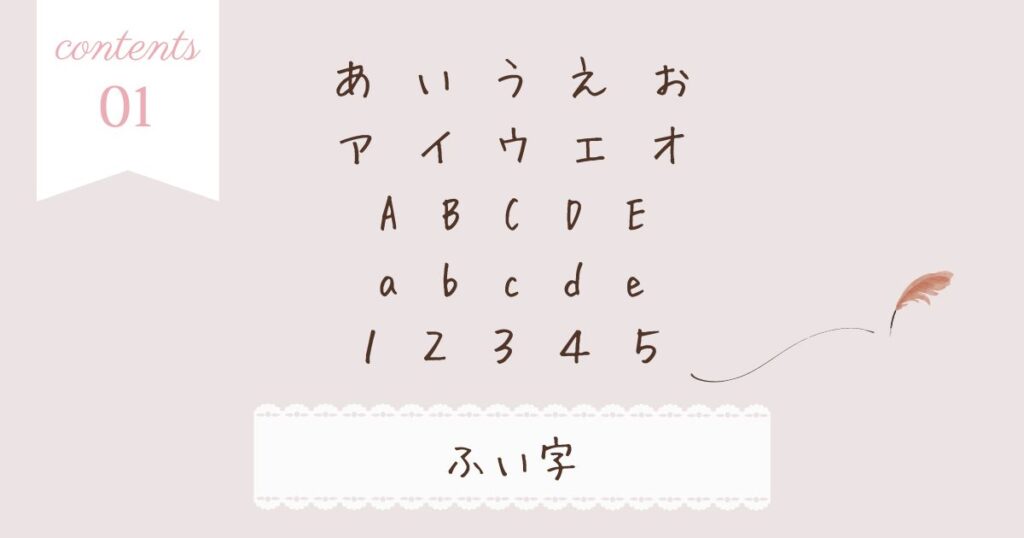
手書きフォントといえば「ふい字」と言われるほど人気のフォントです。
ナチュラルでゆるい雰囲気が特徴で、手紙やイラスト風のデザインにぴったり。
SNSの投稿画像や、カジュアルなバナーにもよく使われています。
手書きの温もりを感じるデザインを作りたいときにおすすめですよ。
うずらフォント
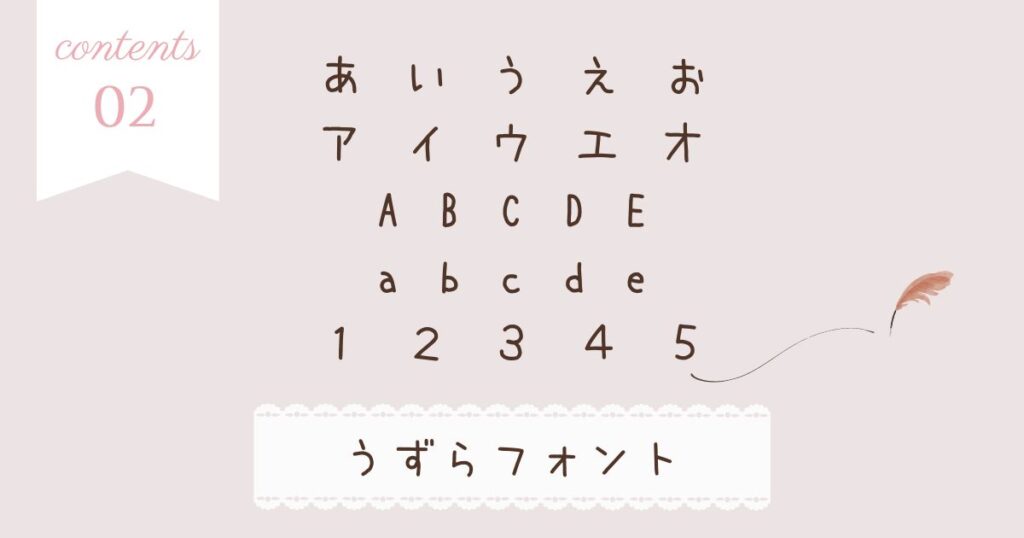
少しクセのある、遊び心のある手書きフォントです。
文字の形がランダムに揺れているため、ポップで元気な印象を演出できます。
子供向けのデザインや、カジュアルなポスターなどに向いていますね。
かわいらしいけれど、しっかり読みやすいのも魅力です。
花鳥風月
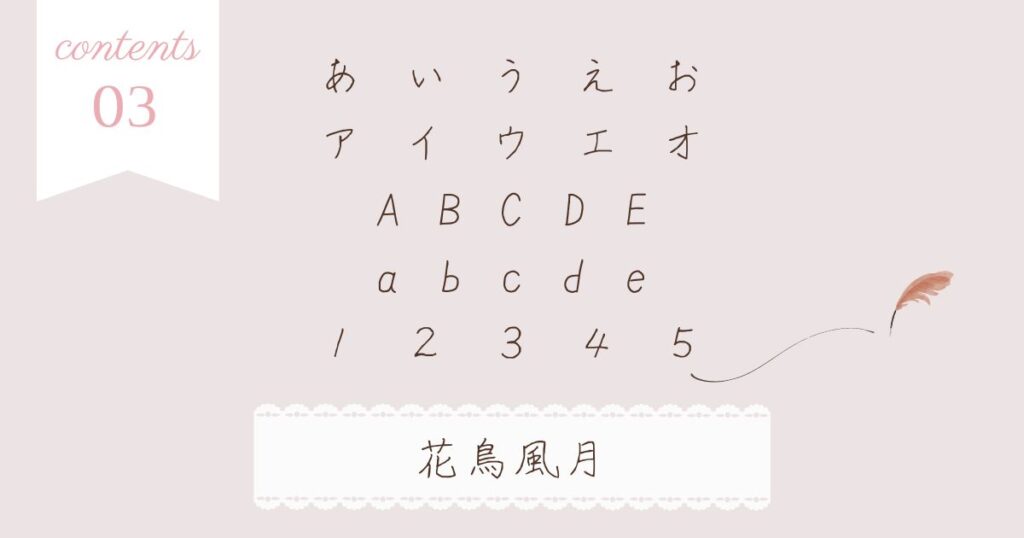
和風デザインにぴったりの手書きフォント。
筆ペンで書いたような柔らかい雰囲気が特徴で、和食のお店のメニューや、和雑貨のパッケージデザインなどに使うと雰囲気が出ます。
上品さと親しみやすさを兼ね備えたフォントですよ。
はなぞめ
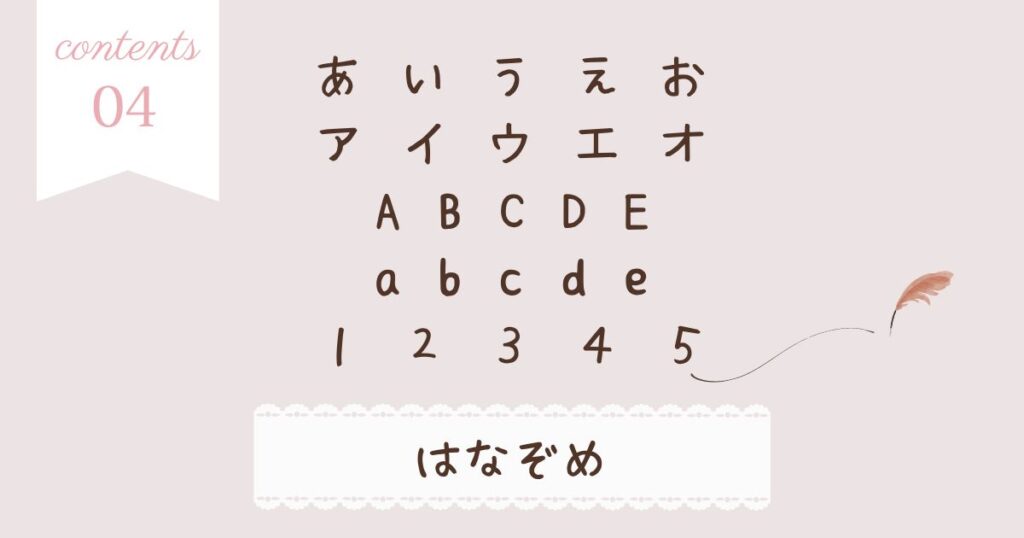
フェミニンでやわらかい印象の手書きフォント。
可愛らしいデザインにマッチするので、女性向けのブランドや、スイーツのパッケージ、インスタグラムの投稿画像にもおすすめです。
女性らしいエレガントな雰囲気を出したいときにぴったりですね。
Sモトヤ行書
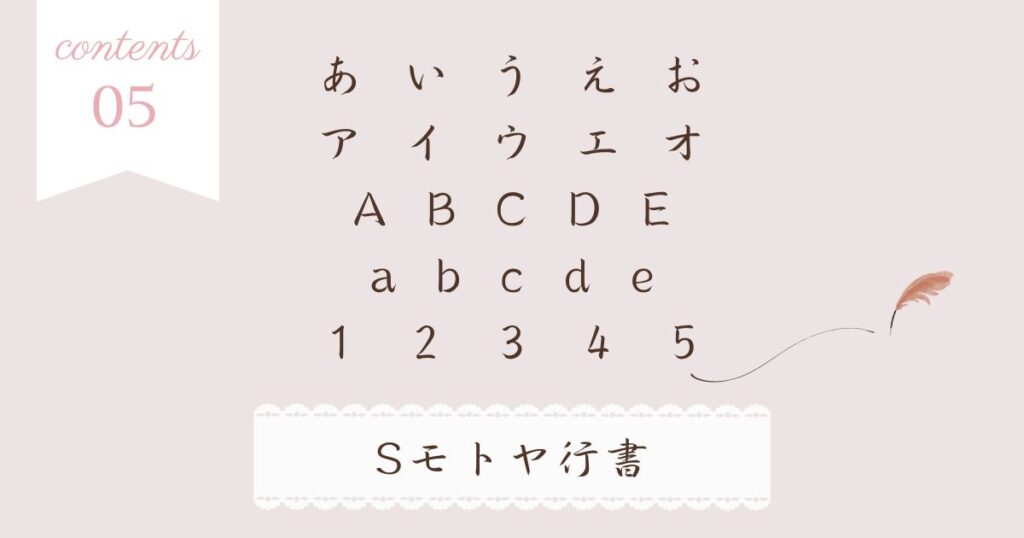
美しい行書体の手書きフォント。
少しフォーマルな印象があり、和風のデザインや高級感のあるロゴに最適。
伝統的な雰囲気を出したいときにもおすすめです。
格式高いデザインを作りたいときに使ってみてくださいね。
じゆうちょうフォント
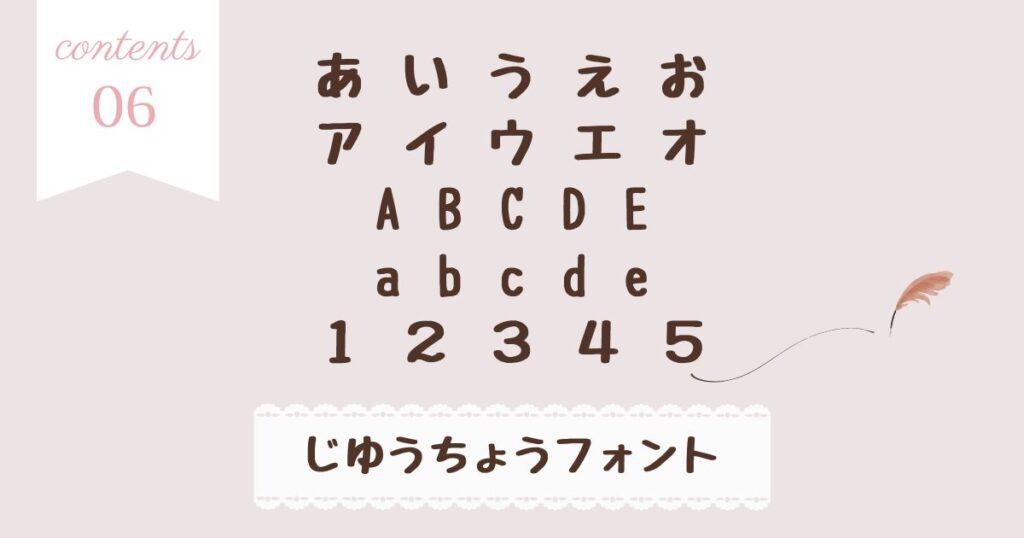
まるでノートに書いたような、ラフでかわいい手書きフォント。
やさしい雰囲気があり、子供向けのデザインや、イラスト系の作品と相性抜群。
手作り感を演出したいときにもおすすめです。
親しみやすいデザインを作るのにぴったりですね。
たぬき油性マジック
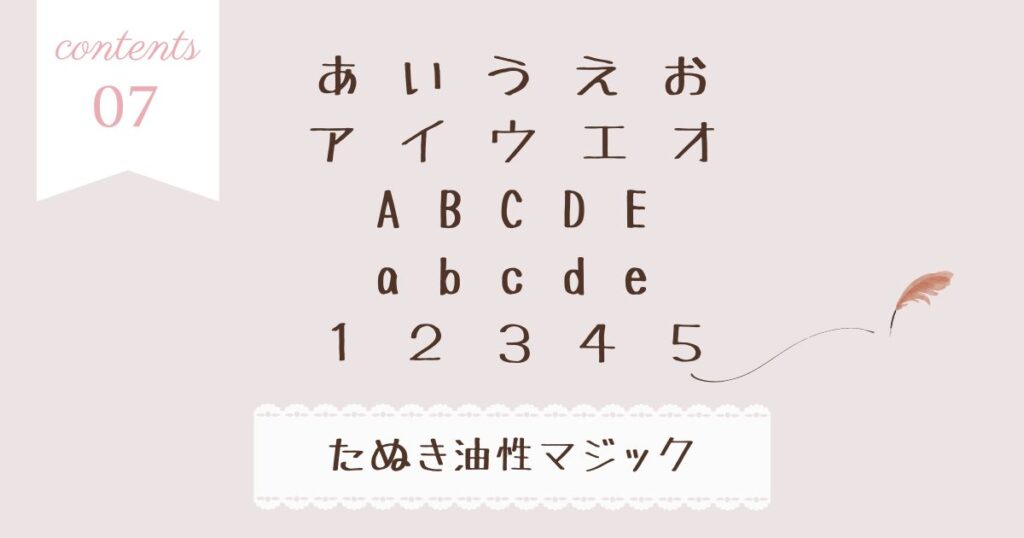
太字で力強い手書きフォント。
油性マジックで書いたような雰囲気が特徴で、目立たせたい文字や、ポップなデザインに適しています。
看板や広告のキャッチコピーにも使えますよ。
インパクトのあるデザインを作りたいときにどうぞ。
デザインの目的に合わせて、最適なフォントを選んでみましょう!
おしゃれなデザイン例と失敗しないフォントの選び方
手書きフォントを使ったデザインは、おしゃれで個性的な雰囲気を演出できます。
でも、使い方を間違えると読みにくくなったり、デザインのバランスが崩れたりすることも。
ここでは、Canvaで手書きフォントを活用したデザイン例や、フォントの選び方、おしゃれな組み合わせ方を紹介します。
Canvaで手書きフォントを活用したデザイン例
手書きフォントを使ったデザインの具体例を紹介します。
実際のデザインを見れば、フォントごとの雰囲気がイメージしやすくなりますよ。
① 大人っぽい上品なデザイン
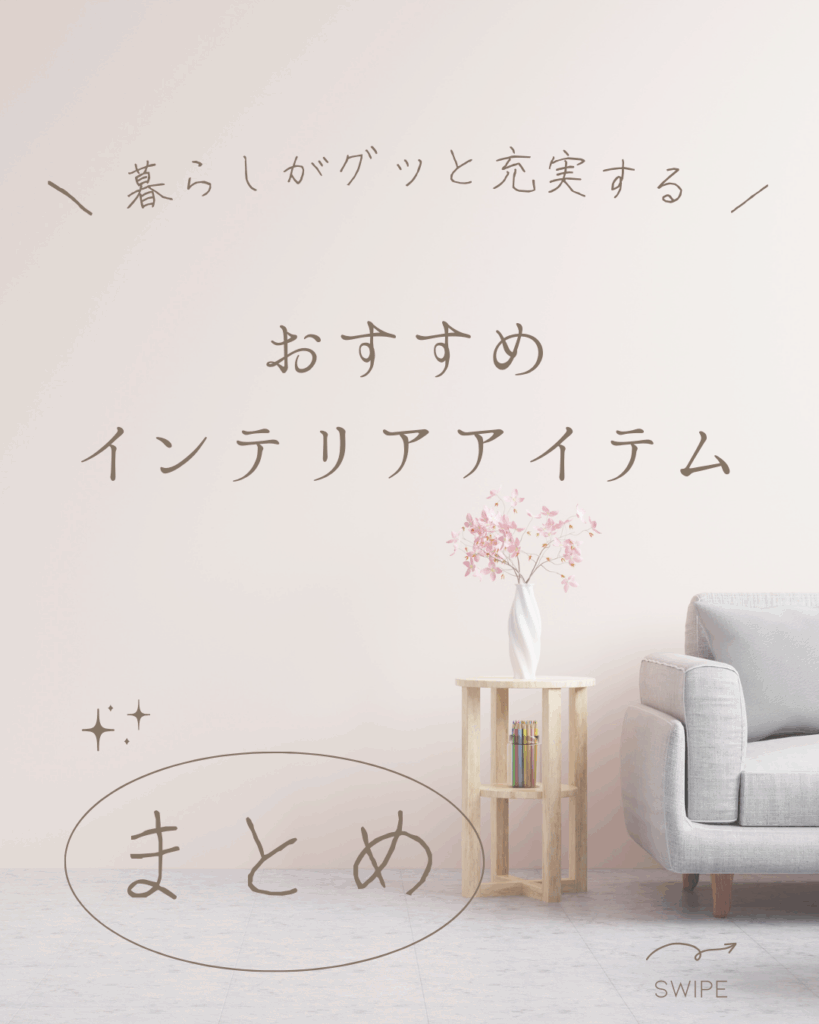
使用フォント:花鳥風月
筆ペンのような上品な書体が特徴。「花鳥風月」を使えば、シンプルでも洗練された雰囲気を演出できます。
② かわいくて親しみやすいデザイン
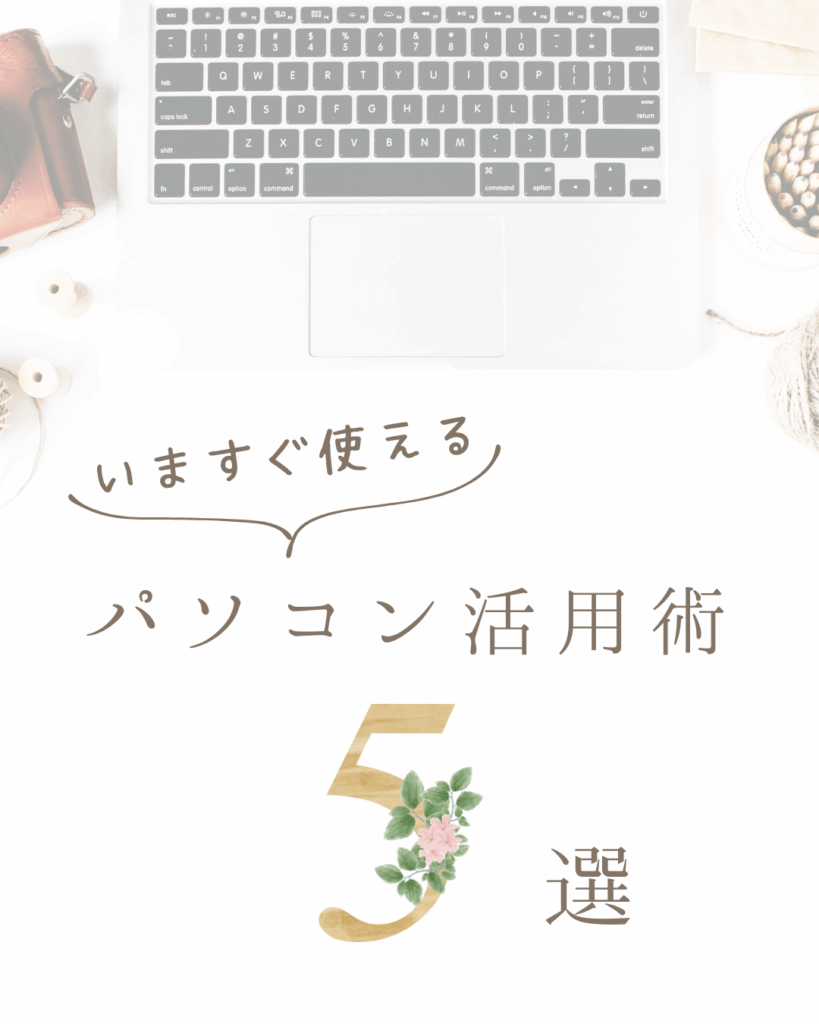
使用フォント:はなぞめ
丸みのある太めの文字が特徴の「はなぞめ」。
かわいくて視認性が高いので、アイキャッチやSNS投稿におすすめです。
③ おとなかわいいデザイン
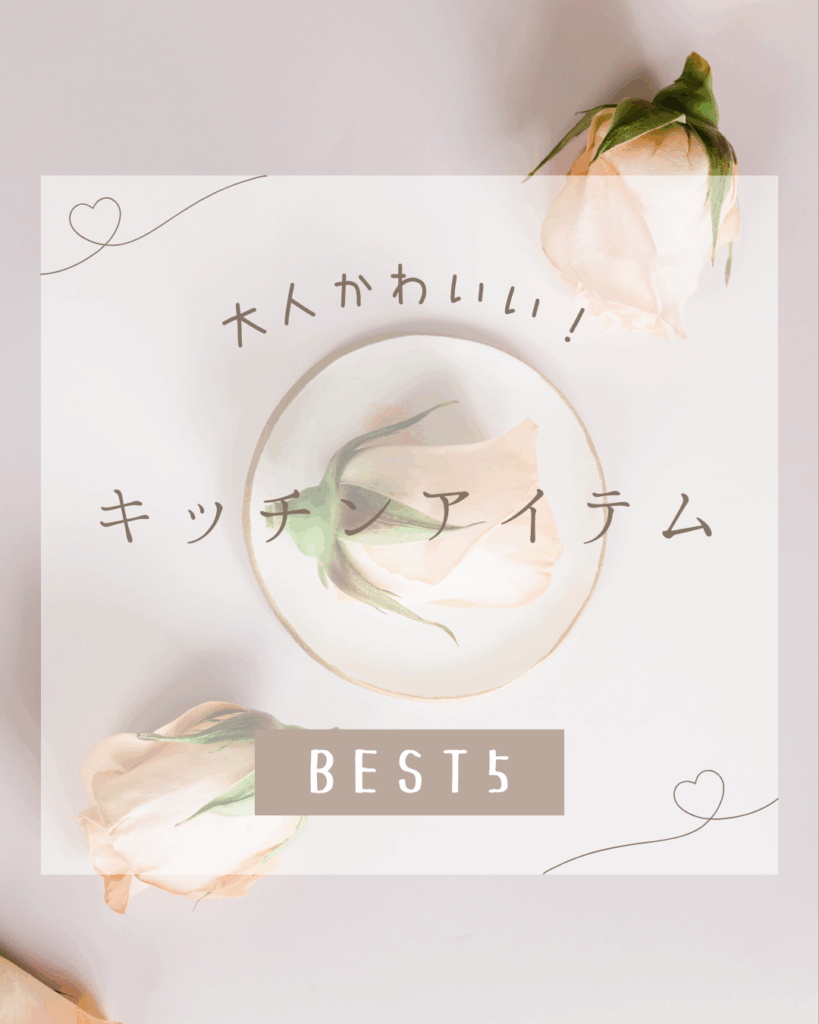
使用フォント:うずらフォント
手書きのラフな風合いが特徴の「うずらフォント」。
シンプルな背景でも、遊び心のあるかわいいデザインに仕上がります。
フォント選びのコツと注意点
- 読みやすさを優先する(細すぎる文字は避ける)
- デザインの雰囲気に合わせる(かわいい・和風・モダンなど)
- フォントのサイズや間隔を調整する(行間を広めにすると見やすい)
他のフォントとのおしゃれな組み合わせ方
- 手書きフォント × ゴシック体:「ふい字」+「Noto Sans」 → ナチュラル&シンプル
- 手書きフォント × 明朝体:「花鳥風月」+「游明朝」 → 和モダンな上品デザイン
- 手書きフォント × 太めのポップ体:「たぬき油性マジック」+「Rounded M+」 → インパクトのあるデザイン
フォントを組み合わせるだけで、デザインの印象が大きく変わりますよ!
まとめ:おしゃれな手書きフォントを使って副業のデザイン力をアップ!
今回は、Canvaで無料で使える、おしゃれでかわいい日本語の手書きフォント7選を紹介しました!
- ブログやSNSに使えるおしゃれな手書きフォント7種類を厳選
- デザイン初心者でも失敗しないフォントの選び方
- 副業に役立つおしゃれなデザインの作り方
看護師の仕事をしながら副業をしている方にとって、デザインは「発信力を高めるための大切なスキル」です。
アイキャッチやバナーが洗練されていると、ブログのアクセスUPやSNSでの注目度も上がりますよ。
Canvaの無料フォントを活用すれば、初心者でも簡単におしゃれなデザインが作れます。
ぜひ今回紹介したフォントを試して、自分らしいデザインを作ってみてくださいね!
デザインのコツをつかめば、副業のブログやSNSがもっと楽しくなるね!
Canvaを活用して、自分だけの魅力的なデザインを作ってみましょう♪